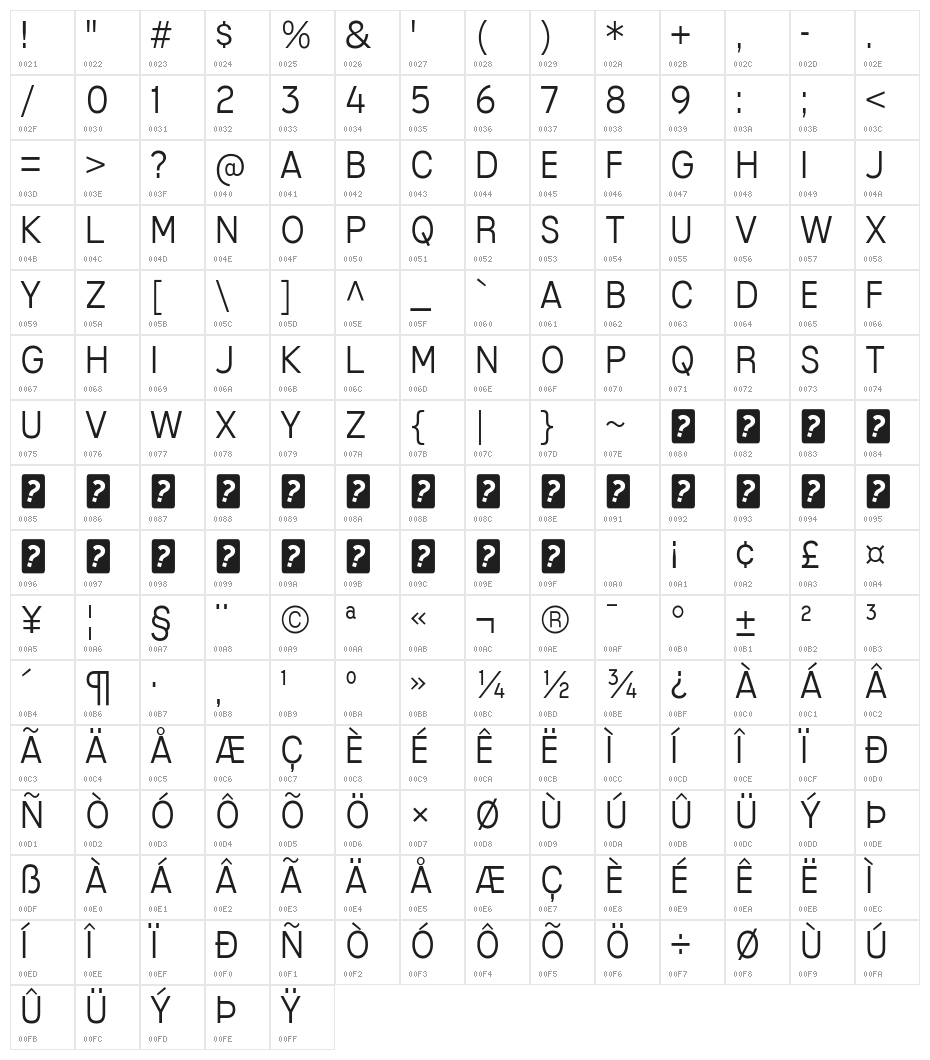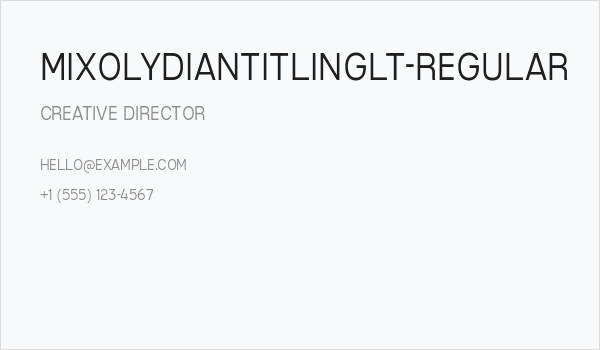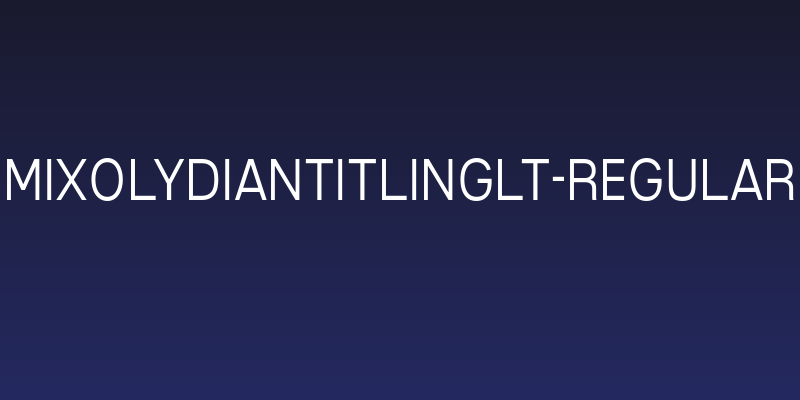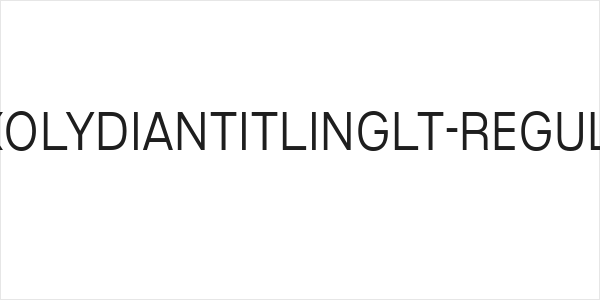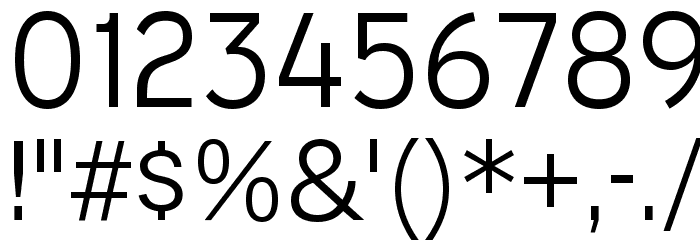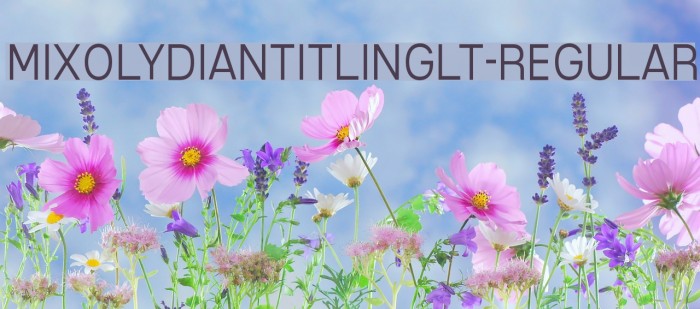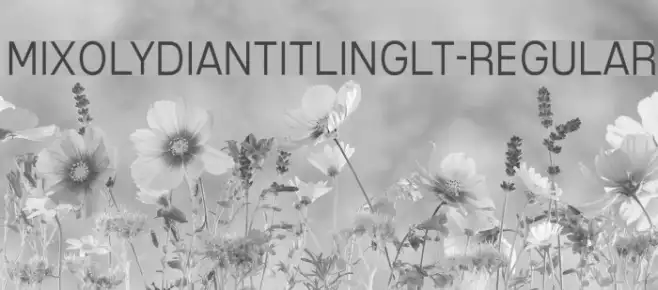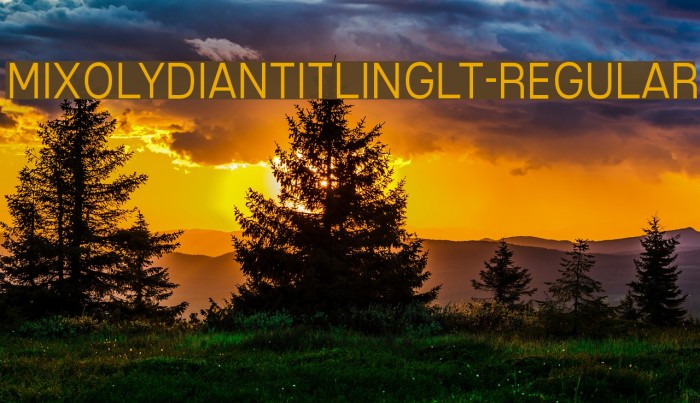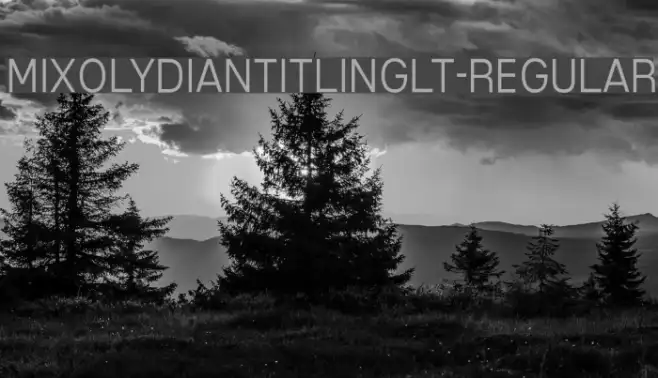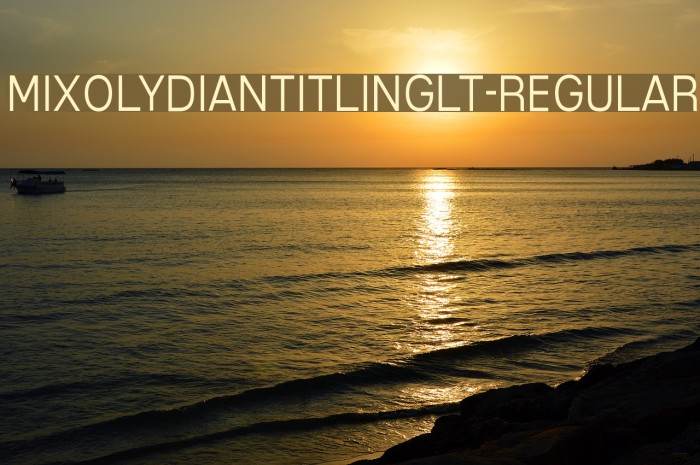
MixolydianTitlingLt-Regular Font
✎ Sans Serif
| Kategorien | Sans Serif |
| Anwendungsfall | Headlines, Body text, Logos |
| Vorgeschlagene Projekte | Ideal for branding, web design, editorial layouts, and signage due to its clarity and modern aesthetic. |